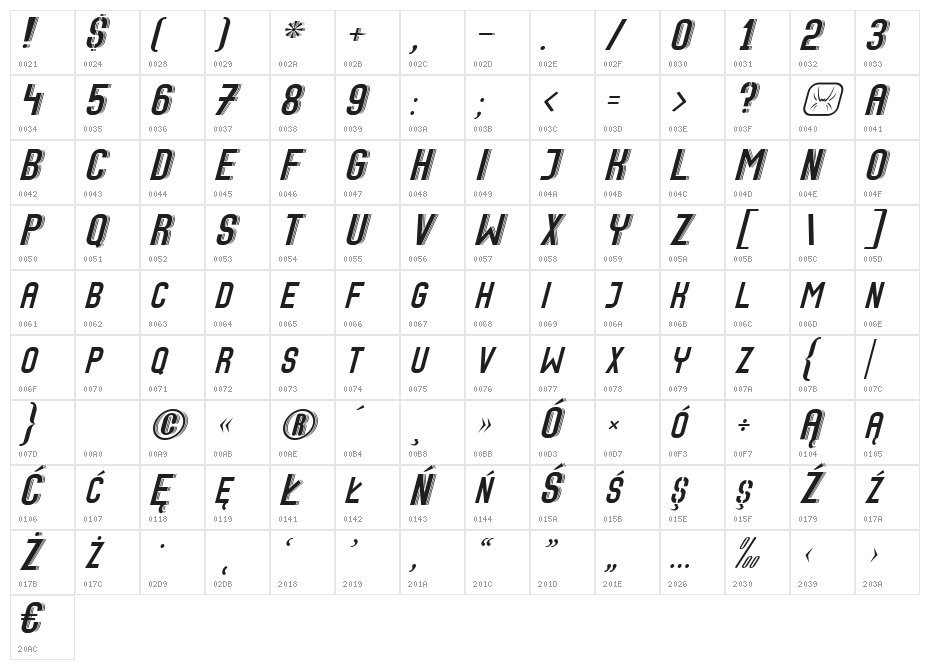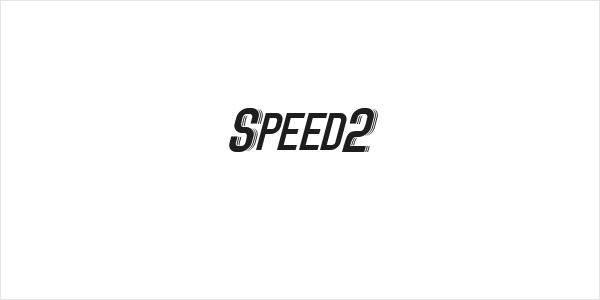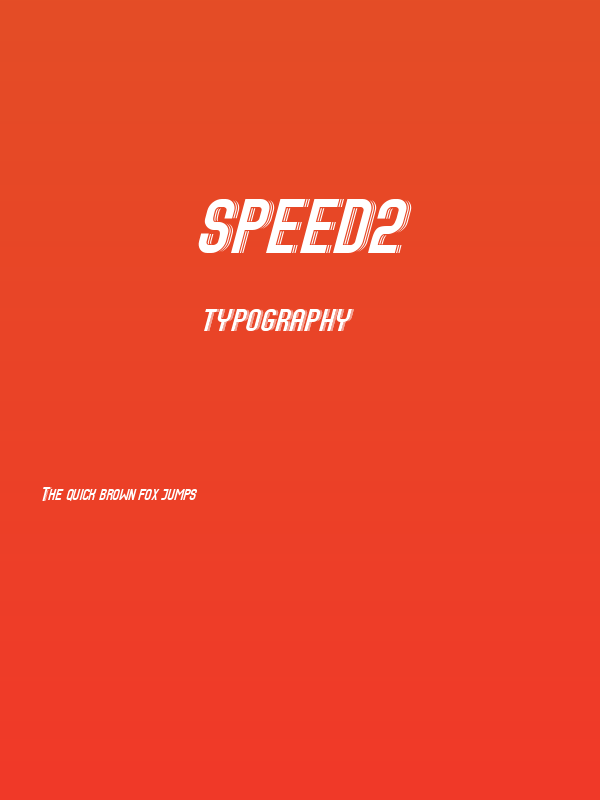
Speed2 Font
| Progetti proposti | Ideal for sports branding, racing event posters, dynamic advertisements, and any project needing a sense of speed and energy. |